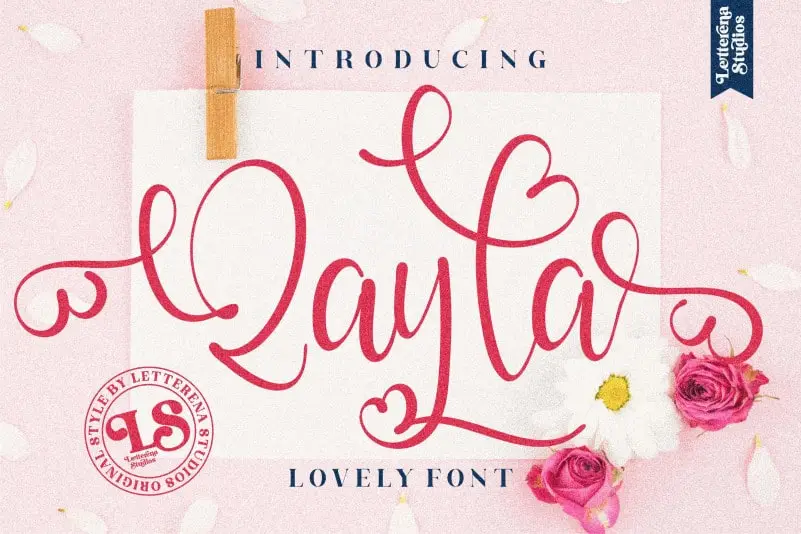
A Qayla Script Font é uma aquarela de letra escrita à mão que transformará seus projetos digitais num destaque entre a multidão. Seu designer especializado, Letterenastudios, criou uma fonte que transmite seriedade e beleza ao mesmo tempo. Desenvolvida para aqueles que valorizam um toque autêntico em suas criações digitais, esta letra escrita à mão é perfeita para gráficos de e-mail pessoal, anúncios nas redes sociais ou até mesmo capas de livro. Ela oferece uma textura encantadora que irá destacar seu trabalho em qualquer projeto. Com a Qayla Script Font, você pode dar vida à sua ideia com um toque único e autêntico. Atrairá os olhos dos seus leitores ou espectadores sem precisar de muito esforço. Seja para uso pessoal ou comercial, essa fonte escrita à mão é perfeita para aqueles que desejam um toque especial em seu trabalho digital.